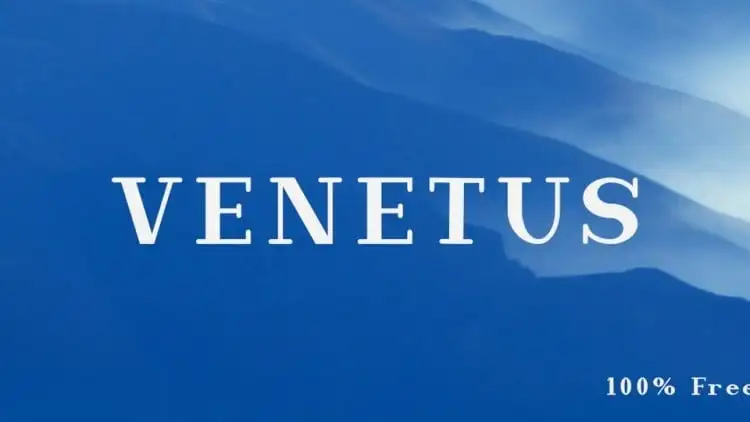
Venetus Serif Font – Download Grátis
Introduzimos a nova Venetus Serif Font !!! Venetus é uma tipografia serif com contraste médio, apresentando formas suaves e um ar quente e macio. Esta fonte se adequa perfeitamente para blocos de texto curtos, headlines e posters. Para aqueles que procuram um toque elegante, sofisticado, classe, chic e modernidade em suas criações, a Venetus foi criada especificamente para você! Suas linhas levemente contrastadas dão ao texto uma aparência envolvente e profissional. Seja em revistas de moda ou sites de design, as letras suaves da Venetus são perfeitas para criar um impacto visual imediato. Experimente a sua versão mais recente e veja como ela pode transformar suas próximas criações!